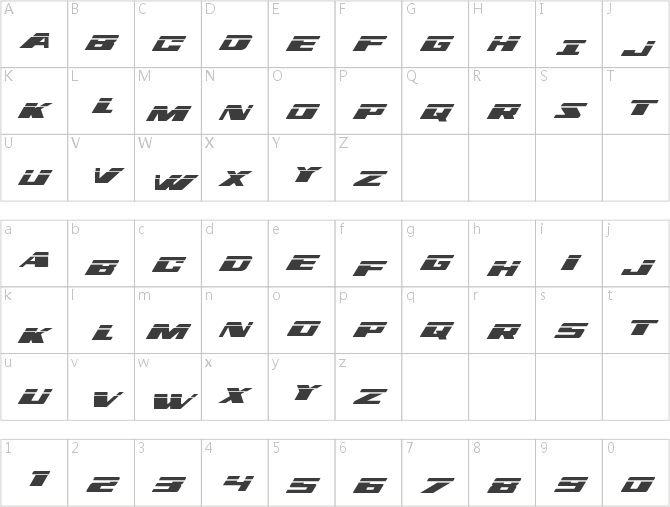
Dassault Laser Italic 詳情頁
Dassault Laser Italic字體字庫是一款讓人賞心悅目、百看不厭的英文字體,適合各類廣告和產(chǎn)品包裝設(shè)計應(yīng)用,字體大小0.03MB,格式為ttf字體,上傳用戶是g05662,作者/版權(quán)方為未知